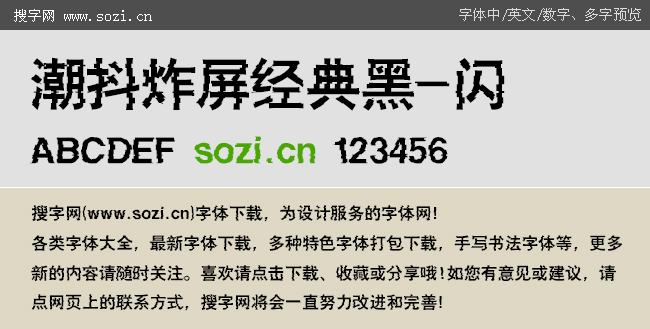
潮抖炸屏經(jīng)典黑-閃
搜字網(wǎng)提供一款潮抖炸屏經(jīng)典黑-閃中文字體下載,潮抖炸屏經(jīng)典黑-閃是一款藝術(shù)黑體字體,潮抖炸屏經(jīng)典黑以黑體字為基準(zhǔn),加入抖動筆畫與切割錯位效果,潮流動感,重新定義時尚字體。適合用于標(biāo)題設(shè)計、海報設(shè)計、包裝設(shè)計等場景廣泛應(yīng)用。(本字體為個人非商用版,商用請聯(lián)系作者購買授權(quán)。官方網(wǎng)址:http://www.reeji.com 聯(lián)系方式:021-58597892)